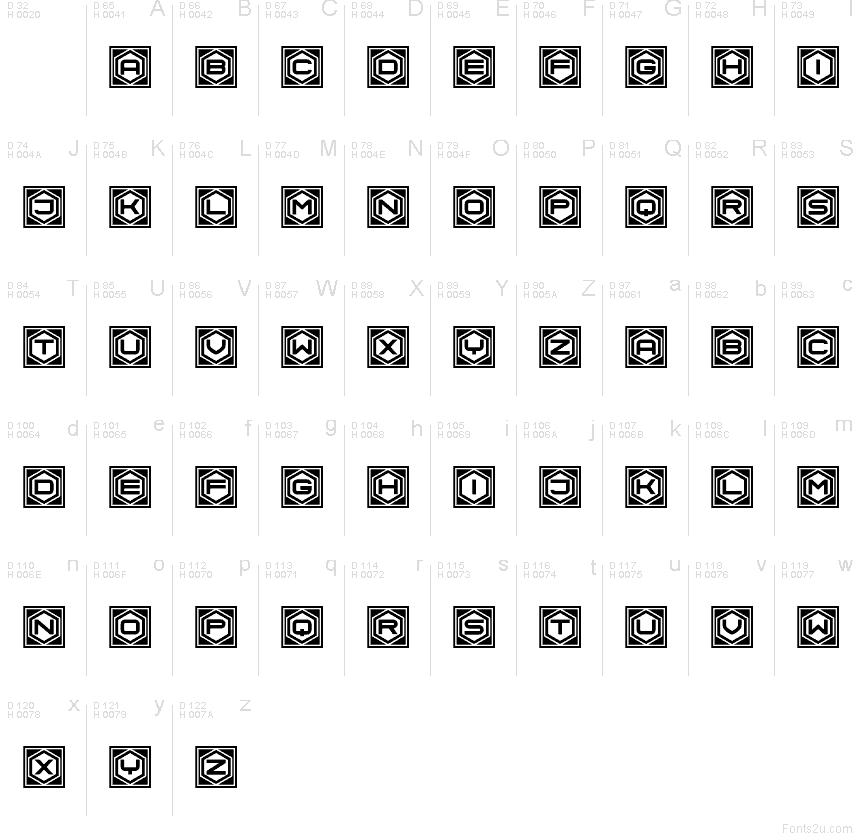
Hexagonas Mira von Vladimir Nikolic ist eine kostenlose geometrische Schrift mit gerahmten Versalien, die auf fetten, von ineinander verschachtelten Sechsecken und quadratischen Rändern umschlossenen Buchstaben basiert. Die wiederkehrende, plakettenartige Struktur verleiht jeder Glyphe die Anmutung eines kompakten Emblems, während scharfe Winkel und einfache Innenstriche an retro-futuristische Kontrollpanels und Arcade-Grafiken erinnern.
Diese kostenlose Schrift eignet sich hervorragend für Science-Fiction-Poster, E-Sport-Logos, Spieltitel, elektronische Albumcover und Technologie-Branding. Sie funktioniert auch bestens bei kurzen Überschriften und Monogrammen, wo die dichten Umrahmungen selbst bei großflächiger Darstellung ihren starken, modularen Rhythmus beibehalten.